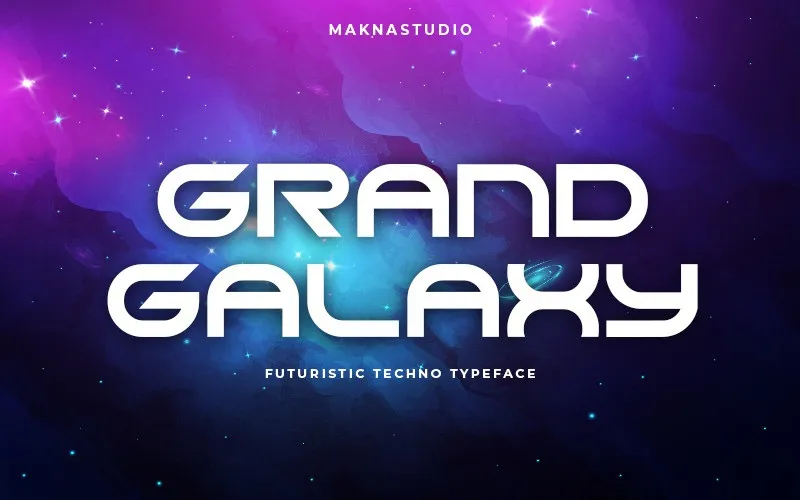
GRAND GALAXY Font – Download Grátis
A fonte ‘Grand Galaxy’ é uma escolha moderna para designers e grafistas apaixonados que buscam um estilo clean e geométrico. Seus caracteres em maiúsculas são projetados para transmitir uma mensagem de robustez e força, idealmente seletos para aplicação em nomes de logotipo como tecnologia, construção, automobilismo ou qualquer outro setor que exija grande impacto visual. Este moderno display font foi criado pela equipe da Maknastudio, uma font designer proeminente no mercado atual. ‘Grand Galaxy’ é perfeito para estilos mais robustos e inovadores em desenho de logotipo. Composta de linhas retas, forma geométrica e um brilho moderno, esta opção não apenas impressionará seu público-alvo, mas também proporcionará uma experiência visual única e memorável ao destacar sua marca.